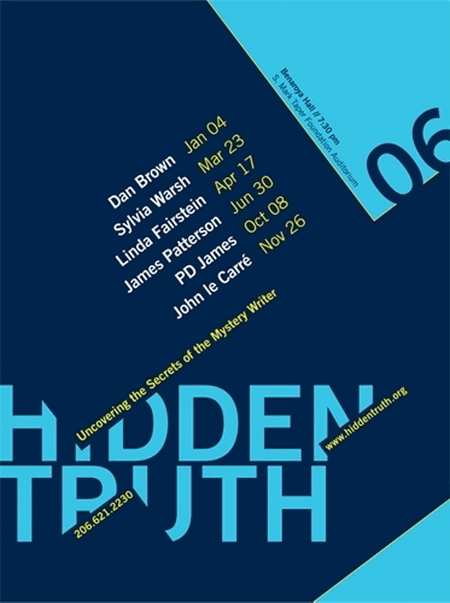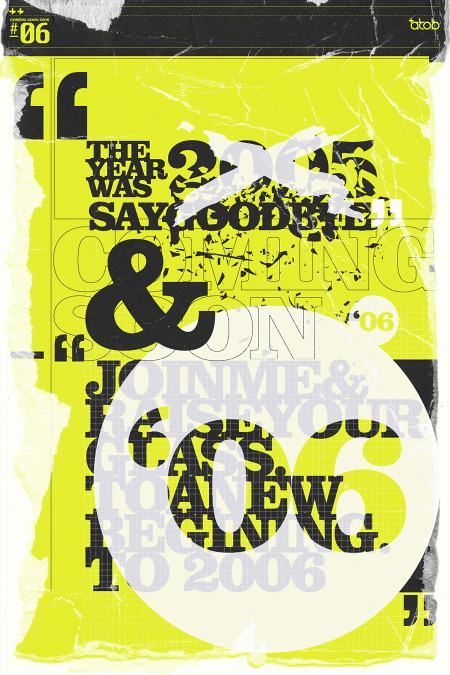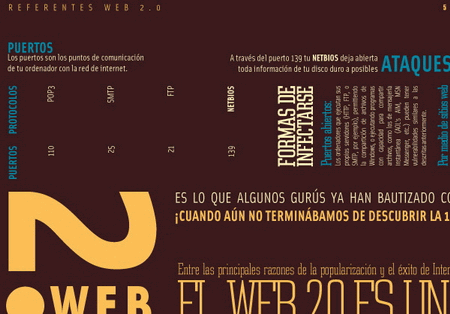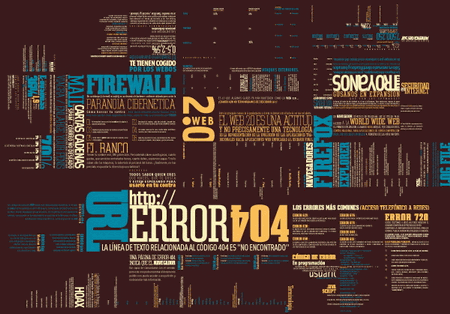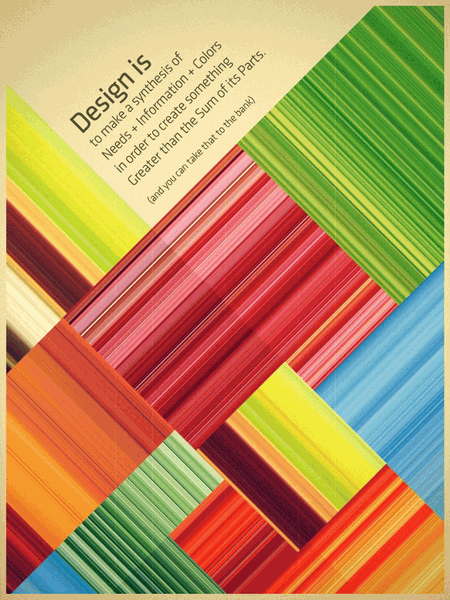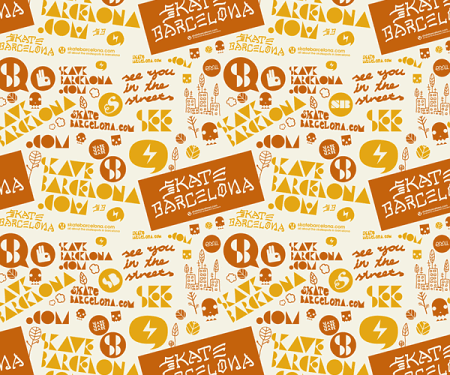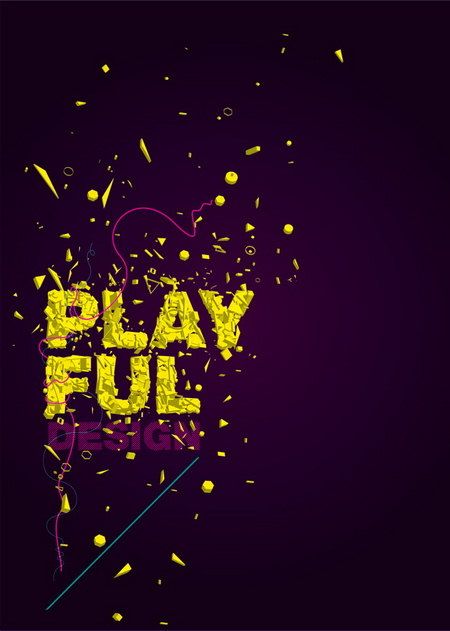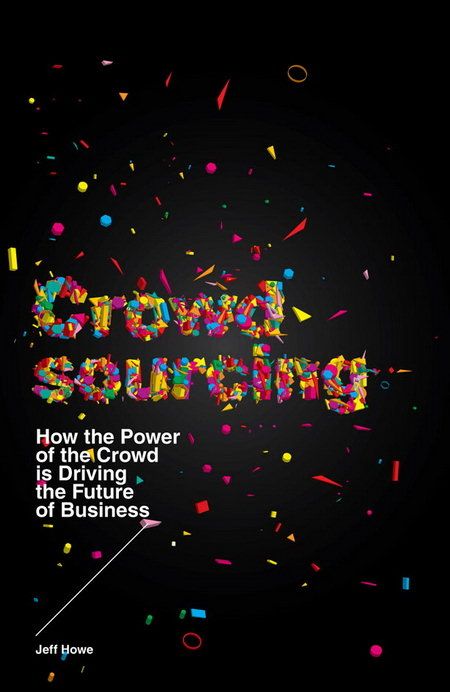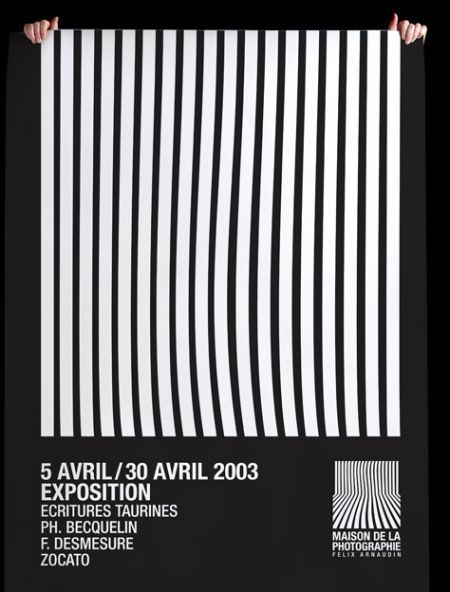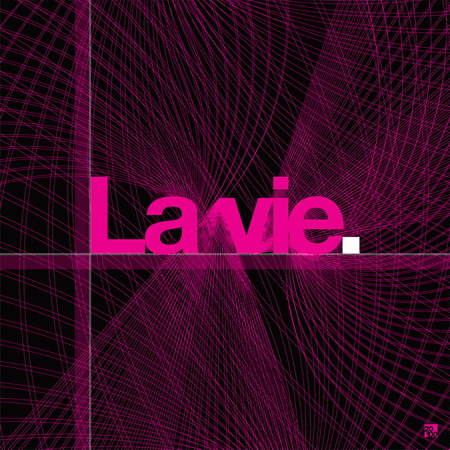
La tipografía como eje del diseño: selección de afiches
No es posible diseñar sin tipografías. Sin embargo, dicen los que saben, sólo es posible utilizar una tipo por diseño, o bien una familia de tipografías. Ahora bien, ¿Cómo lograr un gran impacto y una alta recordación teniendo estas que en teoría, son limitaciones?
De lo que estamos seguros es que suelen ser diferentes de los recursos vsiuales a los que estamos acostumbrados. Así, los diseñadores exploran nuevos horizontes y nuevas perspectivas.
A continuación, más de 20 carteles con diseños que apelan a la tipografía como eje central de su comunicación gráfica. Realizados por artistas de todo el mundo. Oriente, Irán, Japón, China y Rusia entre otros, participan de esta selección.
Christina Koehn / Universidad de Washington, USA.
Alex Banks / Reino Unido
Emiliano Lionel Suárez / Argentina
Juanma Teixidó / Asunción, Paraguay
Emil Kozak / España
Pablo Alfieri / Buenos Aires, Argentina
HeyHo / Francia
Vincent Bousserez / Paris, Francia
Drew Kora / Indiana, USA
Aron Jancso / Budapest, Hungria
Andre Bergamin / Brasil
Oh Ishi / Siam, Thailandia
mrgraphicsguy / Alemania
Puerto Baires / Buenos Aires, Argentina
lee25 / Reino Unido
Piotr Fedorczyk / Florencia, Italia
Noel Tanner / Minneapolis, USA
Kate Andrews / Londres, Reino Unido
Todd Roeth / USA